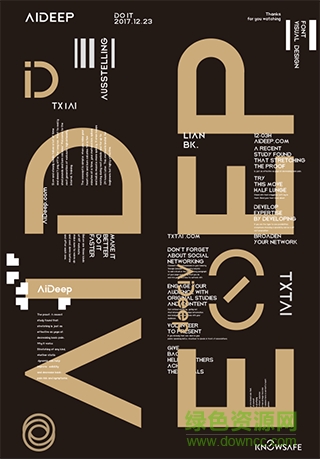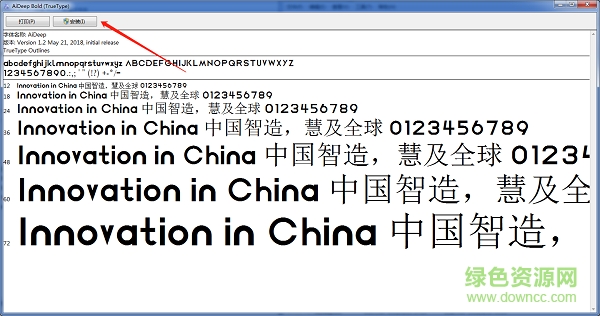
AiDeep字體是一款英文字體,針對26個英文字母做了完整的設(shè)計,用戶可以用戶日常板塊的設(shè)計中,簡約的風(fēng)格中帶有一絲大氣;同時設(shè)計者針對數(shù)字也做了修正,喜歡的用戶快來綠色資源網(wǎng)下載吧!
AiDeep字體是一款開源的字體,由網(wǎng)絡(luò)尖刀用戶體驗中心UED團隊出品,收錄了26個英文大寫字母、及26個英文小寫字母、還有從0到9這10個常用阿拉伯?dāng)?shù)字!